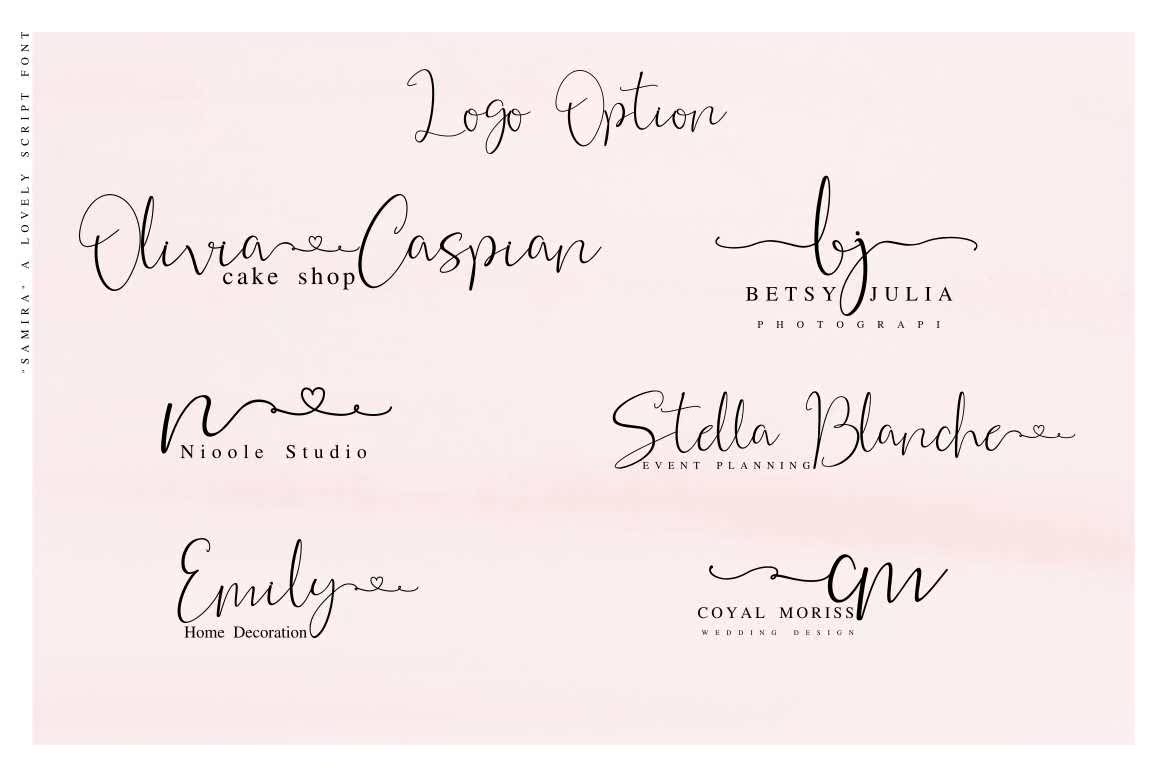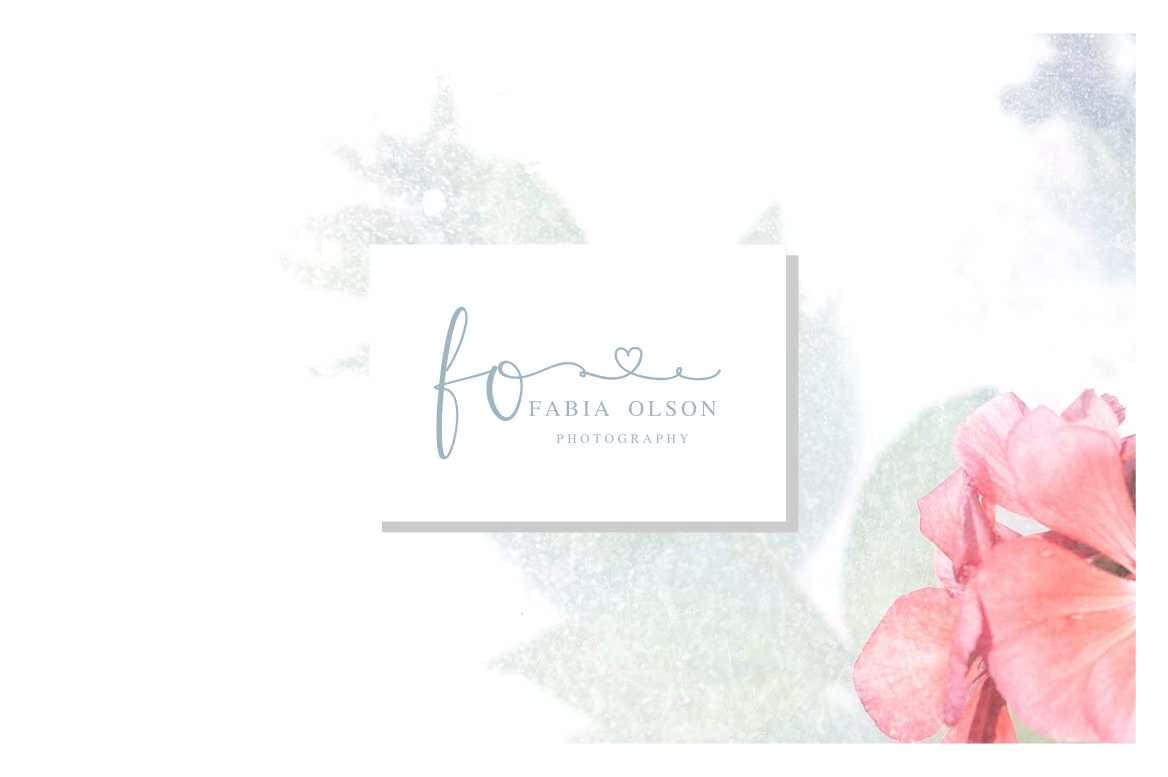
Samira是一款具有手写、复杂流程的现代拼音字体。它包含完整的耳朵和字形。它适用于品牌、婚礼和贺卡。它包括开头和结尾、数字、标点、替换、连字和其他语言🙂Samira是一款具有手写、复杂流程的现代拼音字体。它包含完整的耳朵和字形。它适用于品牌、婚礼和贺卡。它包括开头和结尾、数字、标点、替换、连字和其他语言🙂